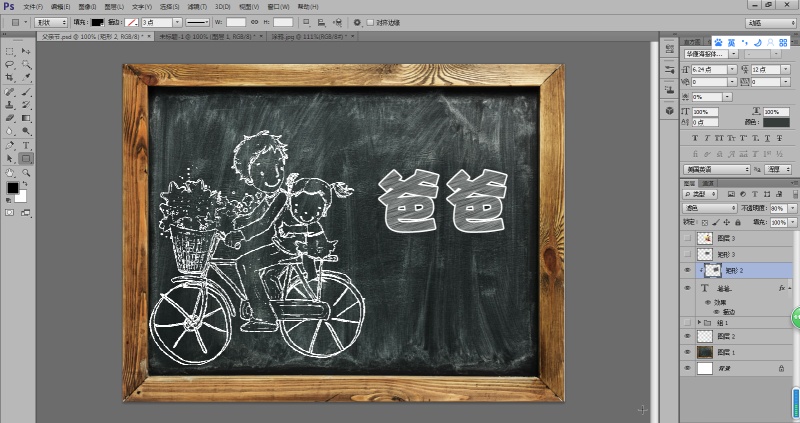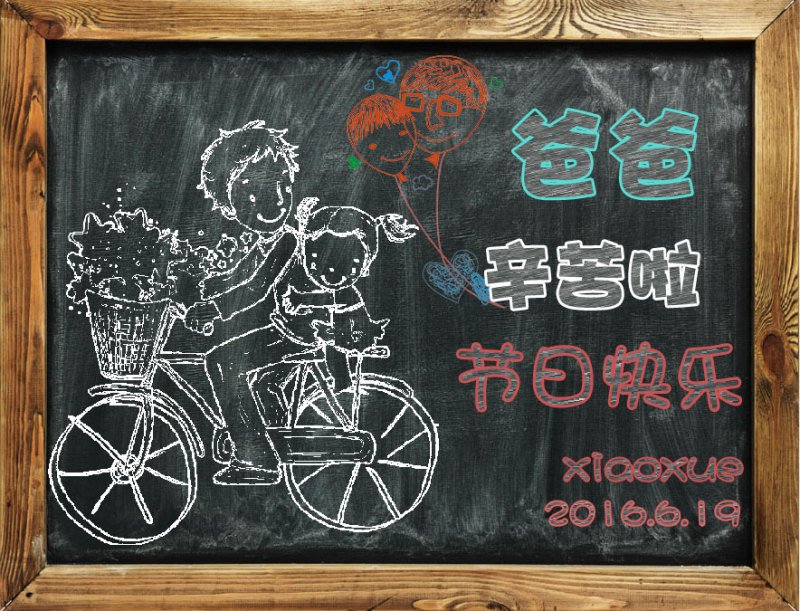
父亲节--粉笔画以及粉笔字体制作教程
马上就要父亲节--父爱如山  制作一款属于自己童年时期的粉笔画以及粉笔字体
下边是左图是通过右图转变后的粉笔画效果
下边我们开始制作父亲节的粉笔画哈
第一步:选一张大家喜欢的图片拖入ps中(因为父亲节快到了,选一张童年记忆的图片啦)
第二步:使用快捷键shift+ctrl+U,图像-调整-去色,然后滤镜--风格化-查找边缘,轮廓就出来了,哈哈~
第三步:使用快捷键ctrl+i,图像-调整-反相,再通过调整色阶,曲线(ctrl+L,ctrl+M)调整,现在粉笔的感觉明显了吧,哈哈哈哈~
第四步:我们现在利用选择--色彩范围--高光(色彩单一的时候抠图还是不错的方法)来扣这个粉笔画,然后放在一块黑板上边,是不是粉笔画的效果就出来了。
第五步:现在我们再来讲一下怎么设计粉笔字(有的可以下载,可是字体会受到限制),所以我们可以用下边的方法来制作自己喜欢的粉笔字体哦。 先写好自己喜欢的字,选择好字体,字体颜色选择与黑板相近的颜色,加描边(如图):
第六步:利用矩形选择工具画一矩形(如图);接着滤镜-杂色--添加杂色(如图):
第七步:滤镜-模糊-动感模糊,然后ctrl+T,旋转一定的角度,混合模式改成滤色
第八步:将动感模糊后的图层剪切到文字层(如图),粉笔字就做出来了,可以更换不同颜色的字体,哈哈,接着设计一下,父亲节马上到了,我们做一张童年回忆的粉笔画吧。